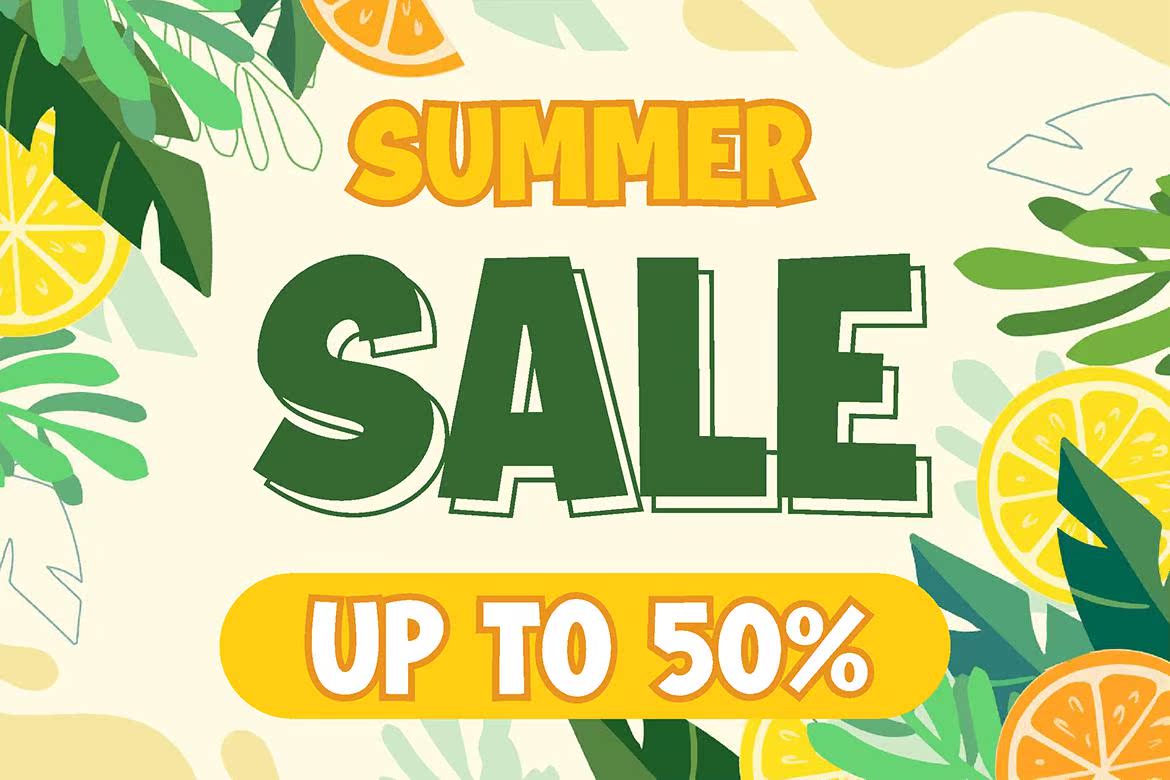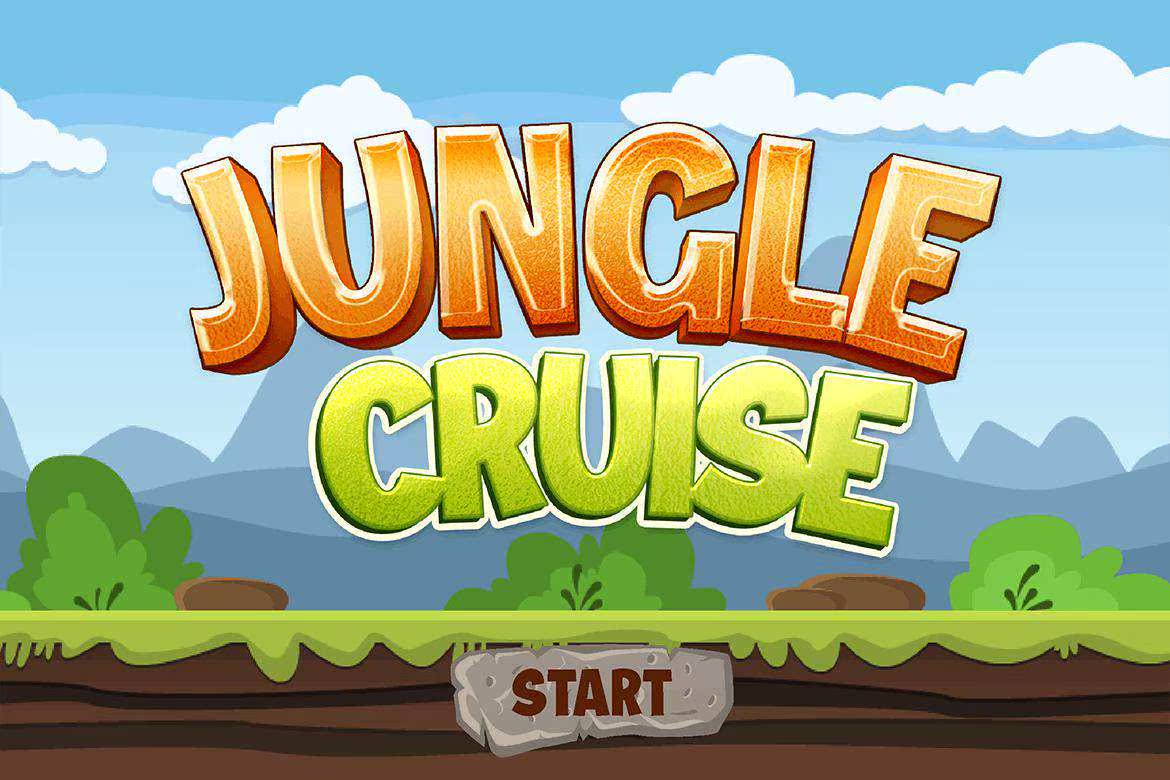
使用带有锐角的强有力的Sternsans衬线的粗体造型,将使JungLeader Venturer在屏幕上的每一个角落都能突出重点。非常适合在线游戏、海报、电影、快餐菜单、杂志、YouTube封面、YouTube缩略图、社交媒体封面以及不久的将来……使用带有锐角的强有力的Sternsans衬线的粗体造型,将使JungleAdventurer在屏幕上强调每一个方面。非常适合在线游戏、海报、电影、快餐菜单、杂志、YouTubecover、youtubethumbnails、社交媒体封面等…